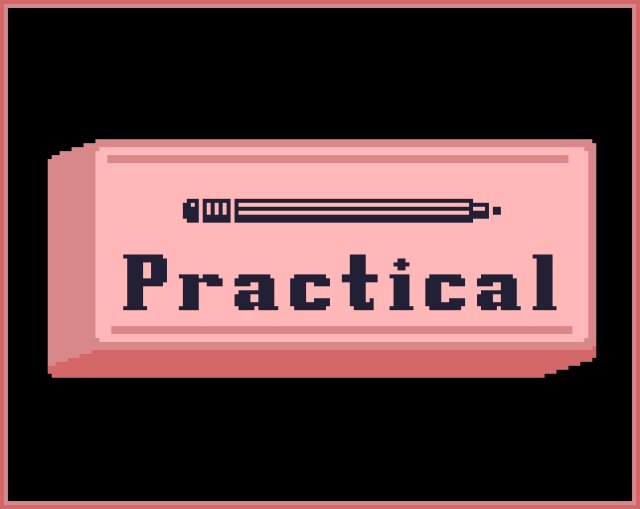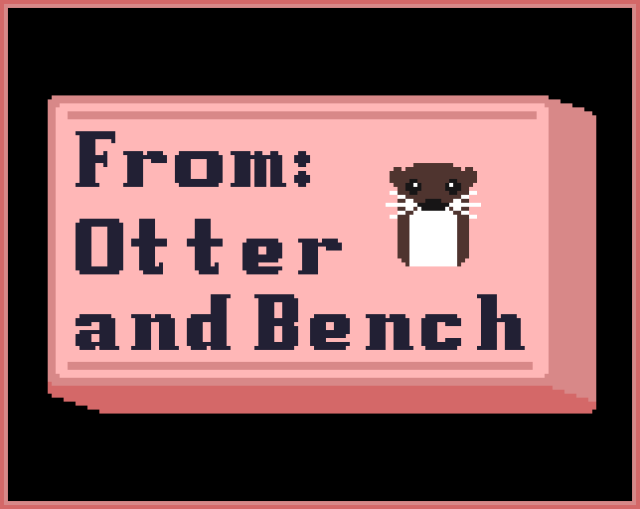
免费的16*16简约像素衬线字体素材,下课后,按照老师的指示,拿起粉笔在黑板上写字。
实用包括以下字符:
ABCDEFGHIJKLMNOPQRSTUVWXYZ
abcdefghijklmnopqrstuvwxyz
.!?:,;@#$%^&*()-_=+[]{}|\/
‘”`><0123456789¡¿ÁáÀàĀāâ©
КамаÉéÈèĒēÊêËëẼẽÍíÌìĪīÎîÏï
乌鲁木齐
Ææβẞ€$¥$Ññ×÷·Ÿß§ÇçşşḨḩŞşŢţ
ⱿɀⱮɱ…¢~¤°±≈≠∞→←↑↓■□●○ŐőŰű₽